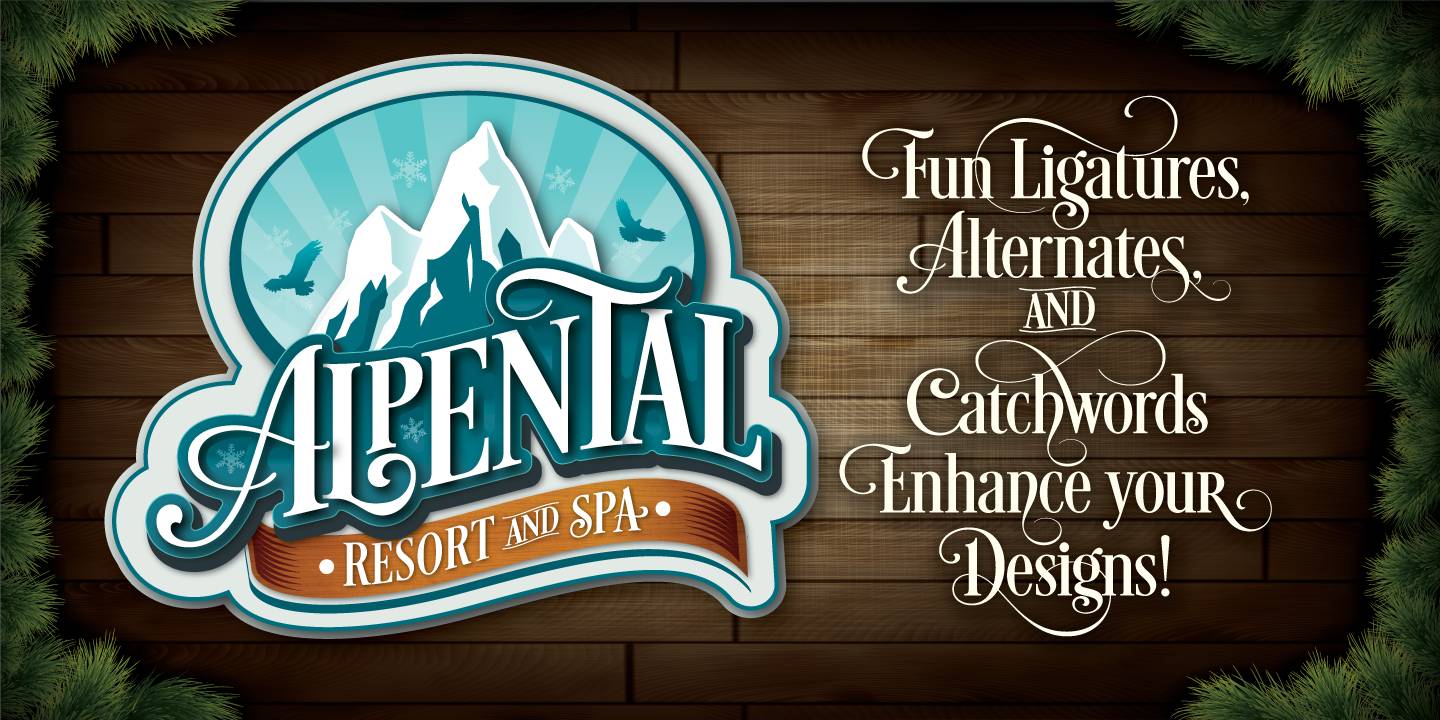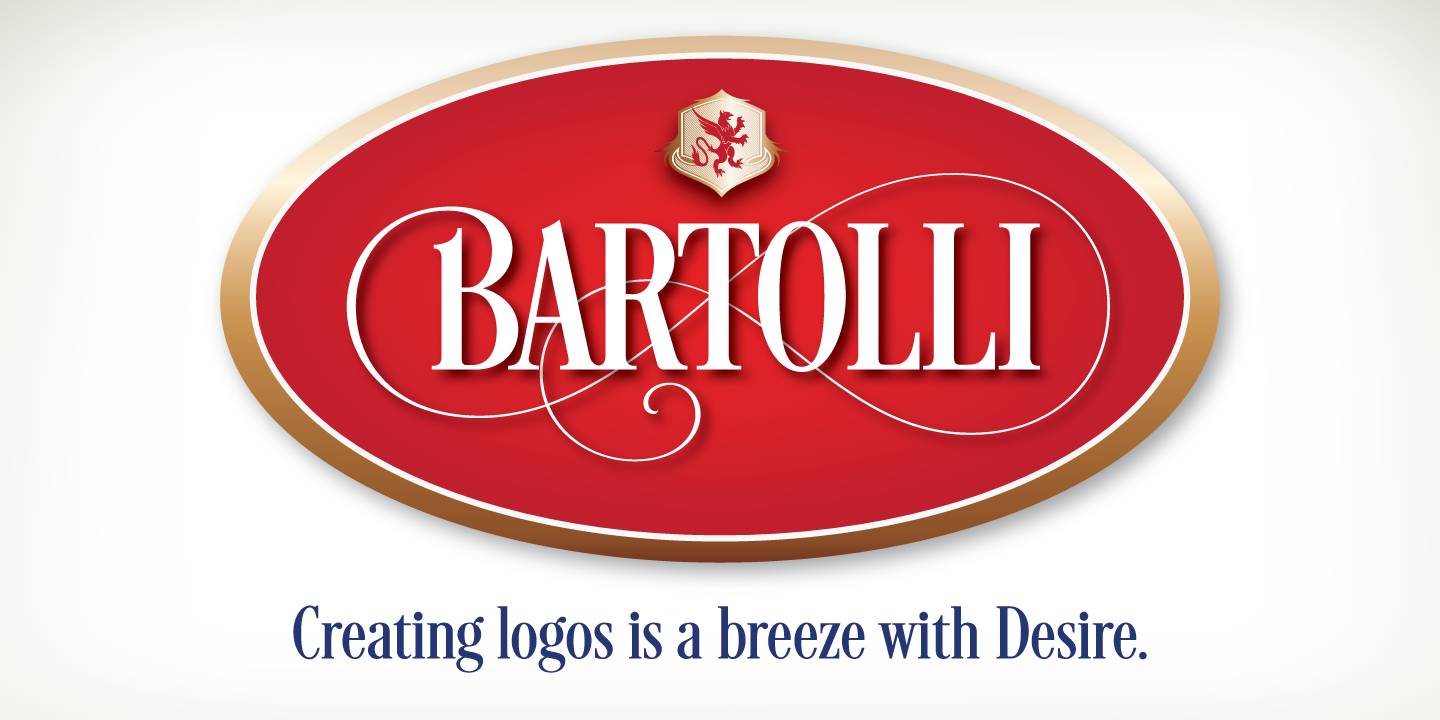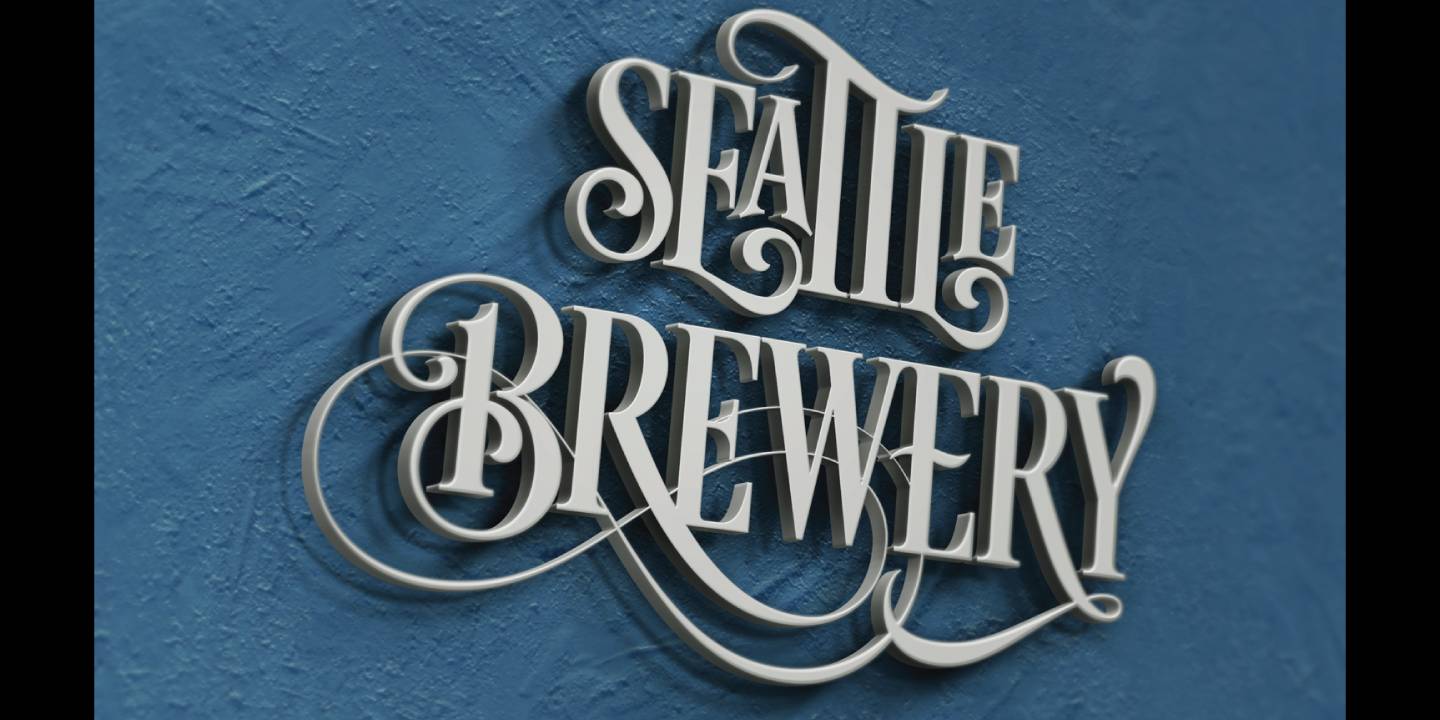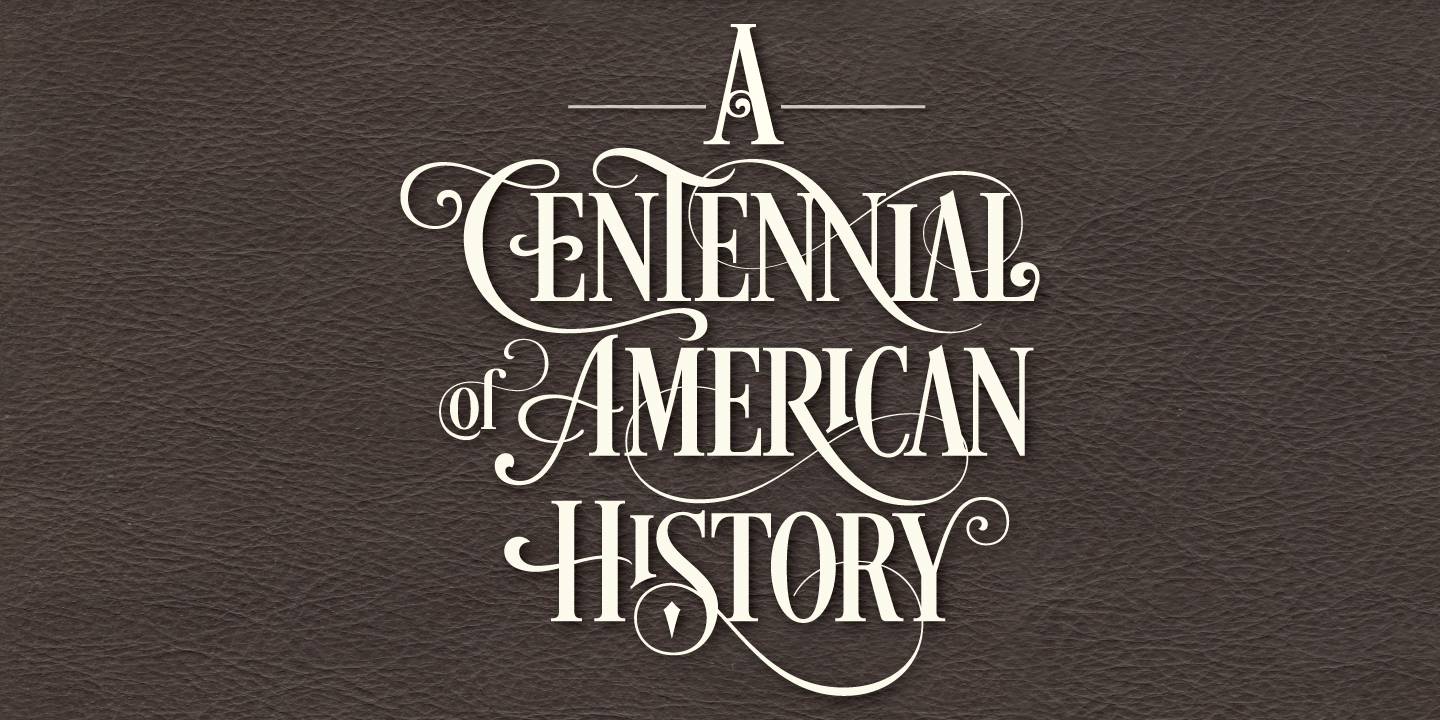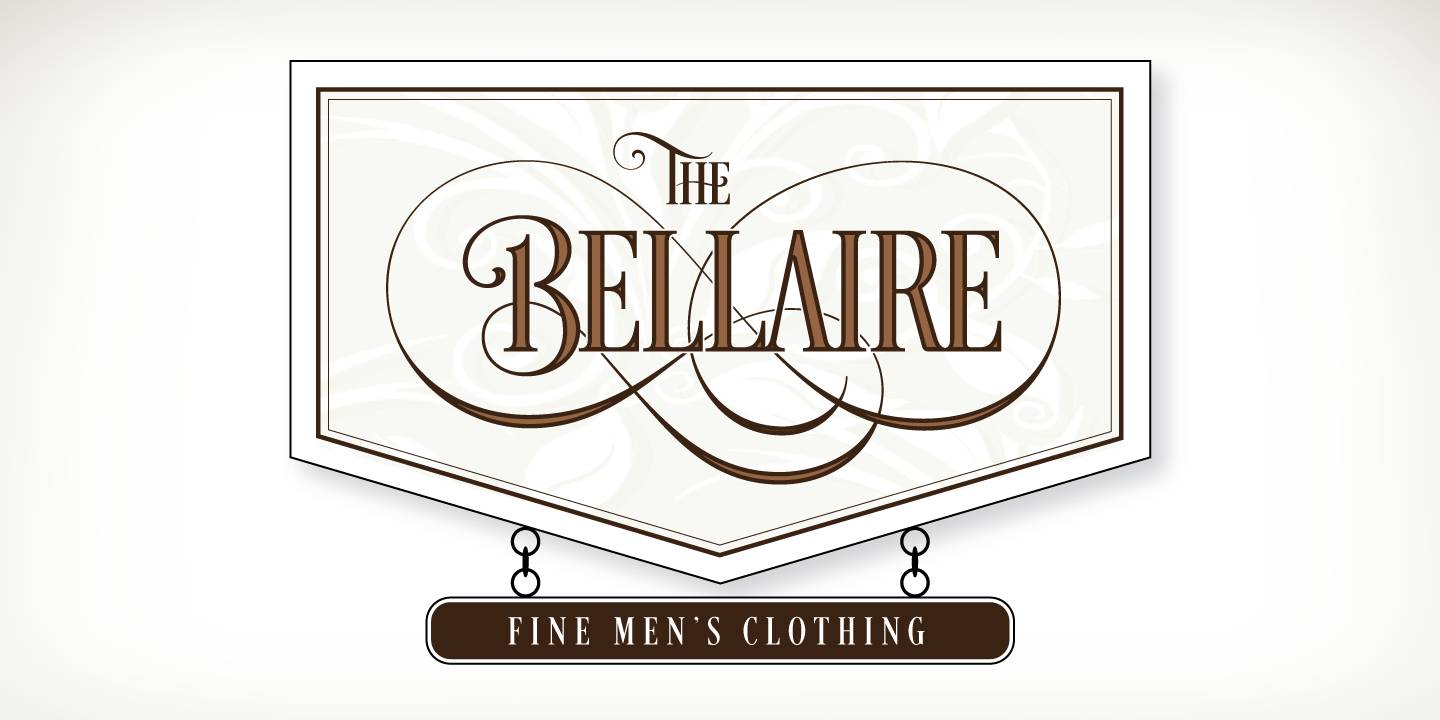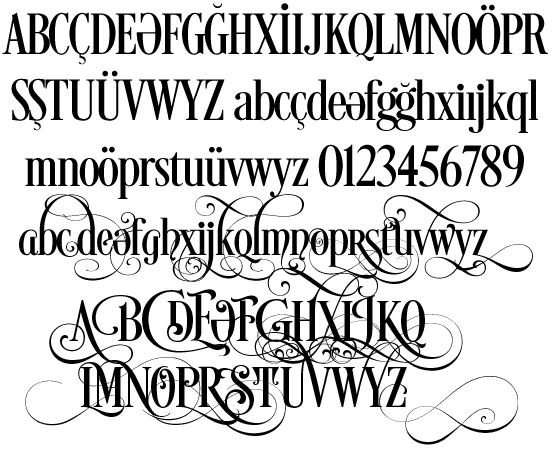
2013-cü ilin ən çox bəyənilən bu elegant font dizayner Charles Borges de Oliveira tərəfindən tipografiyaya verilərək, xüsusən logo dizaynerlərinin vazgeçilməz seçimi olmuşdur. Condensed əsasında olan font özündə həm ciddiliyi həm də kaliqrafik üslubları birləşdirir. Elə fontun qeyri-adi özəlliyi də bundadır: tək font endirib-qurmaqla istədiyiniz hərflərin kaliqrafik bir neçə alternativini seçərək yazıya incəlik qata bilərsiniz.
Bununçün, charmap programından vəya aşağıda izah olunan professional programlardan istifadə edə bilərsiniz. Xatırladım ki, fontun sonuna həm böyük, həm də kiçik "Ə" hərfləri üçün 5 ədəd variant əlavə edilib.